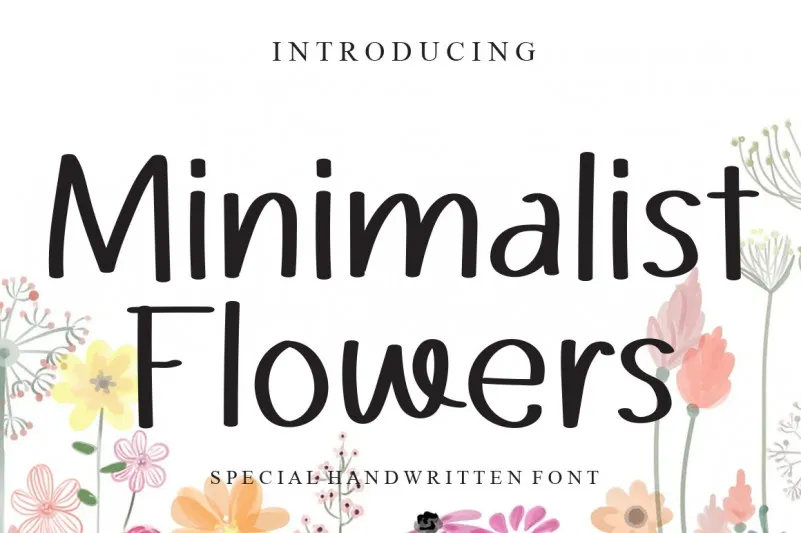
Minimalist Flowers Font – Fonte Grátis
Minimalist Flowers Font
A Minimalist Flowers Font é uma elegante fórmula de escrita manuscrita que traz para você uma sensação leve e descontraída. Com suas linhas curvas limpas e claramente legíveis, esta fonte é perfeita para quem busca dar um toque especial em seus projetos criativos. Ela parece flutuar acima do resto, oferecendo um visual de outra dimensão aos seus designs, seja eles pequenos detalhes ou grandes obras de arte. A LevinCreative nos presenteia com uma fonte que se conecta ao coração da criatividade, fazendo-nos querer usar essa delicada escrita manuscrita em nossos trabalhos mais inovadores e originais. Sua beleza não só tornará seus projetos únicos, mas também certamente os tornará um ponto de destaque no mundo do design visual.